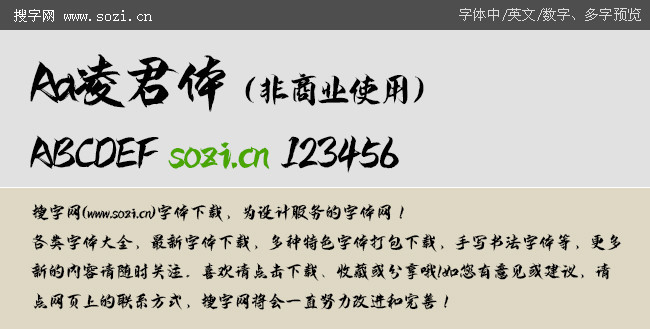
Aa凌君體
搜字網(wǎng)給大家提供一款A(yù)a凌君體(非商業(yè)使用)中文字體下載,該字體是一款手寫風(fēng)格的字體,字體筆觸適中,書寫流暢,字形灑脫,具有很好的視覺感。適合書裝設(shè)計(jì)、包裝設(shè)計(jì)、海報(bào)設(shè)計(jì)等應(yīng)用(此字體為個(gè)人非商用版,商用可以聯(lián)系QQ:1006760504)。